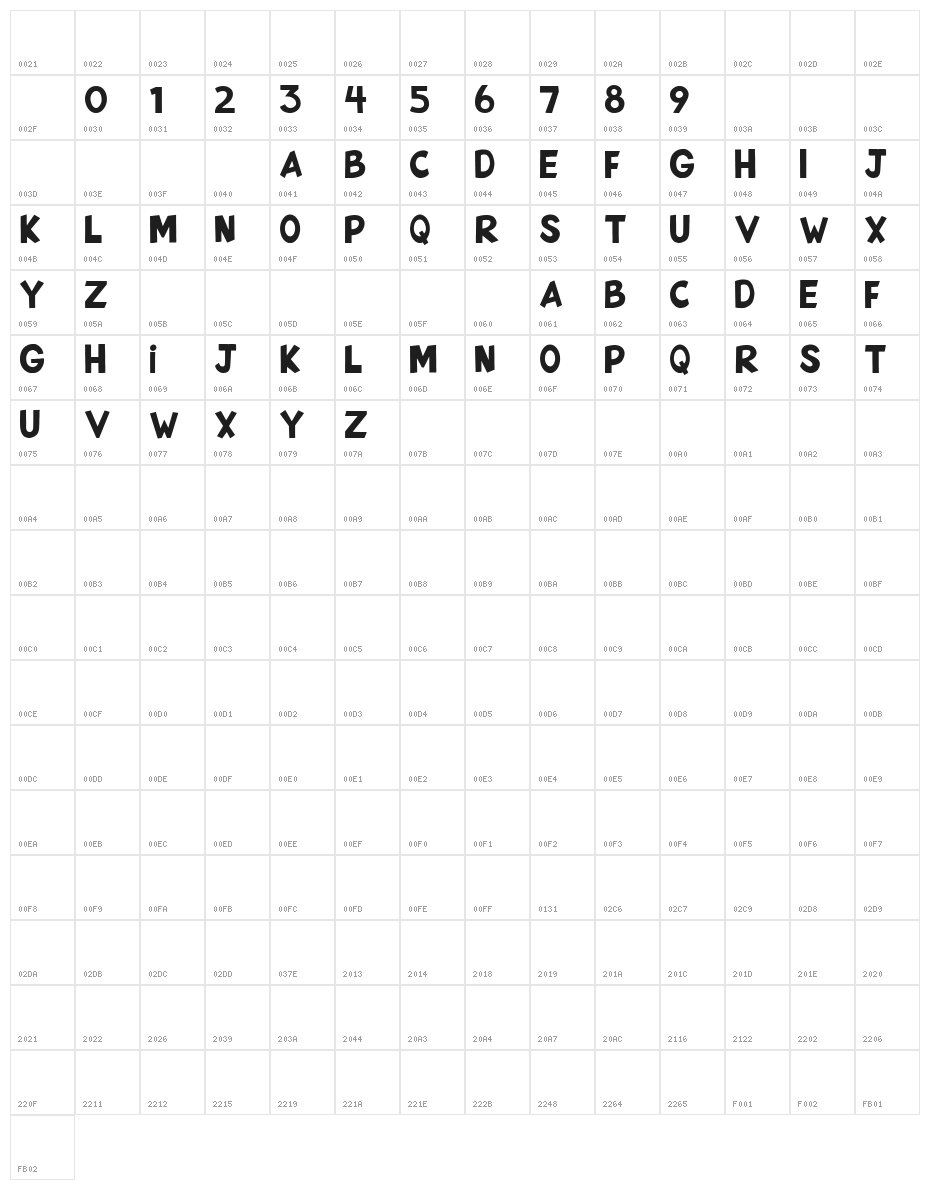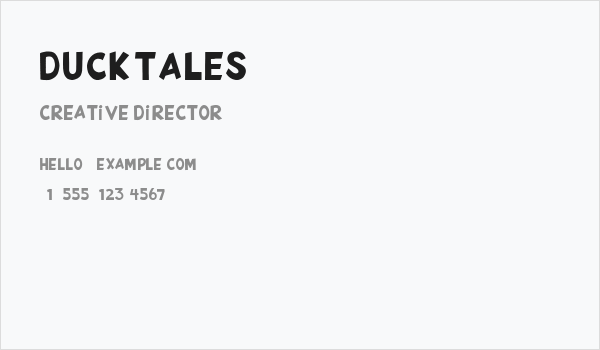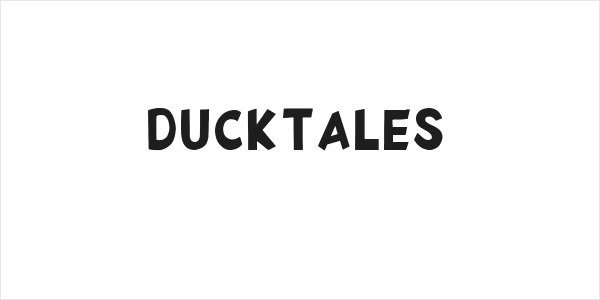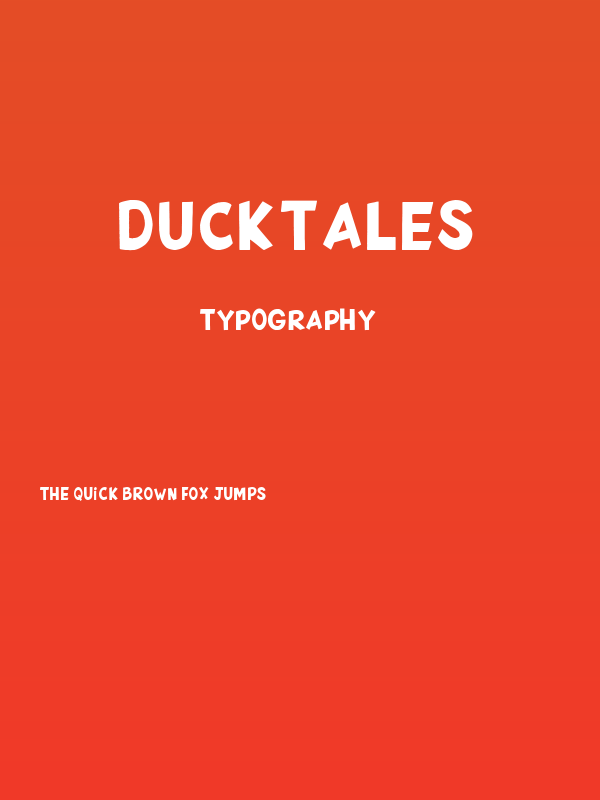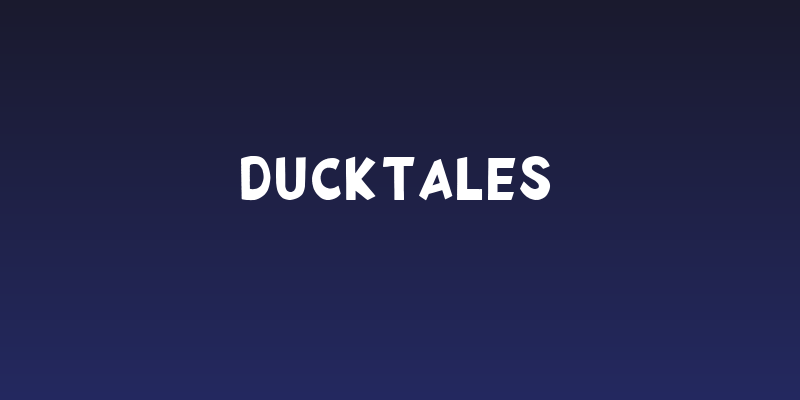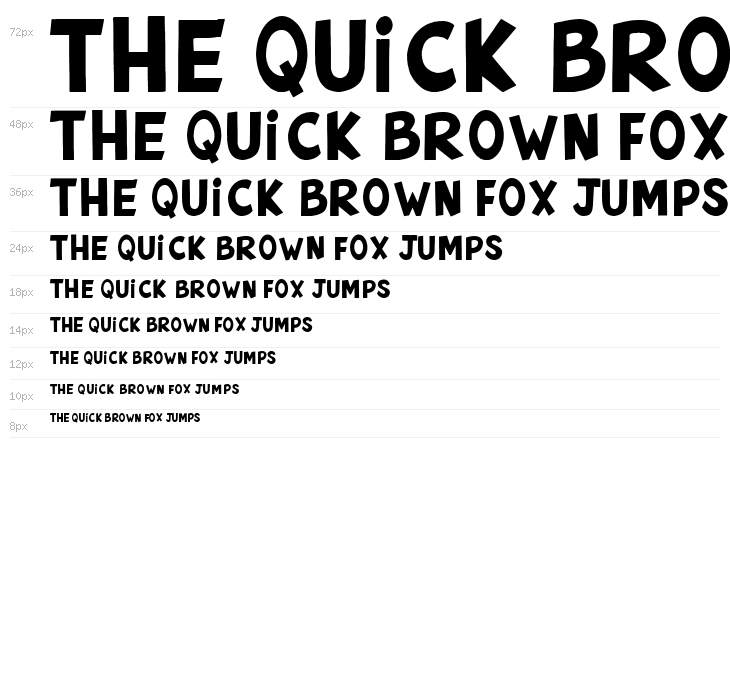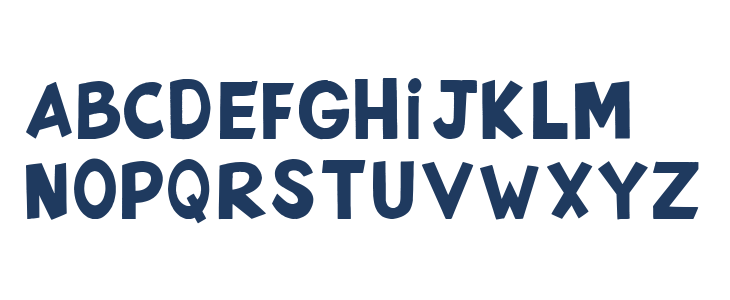
DuckTales Font
| 整体风格 | Playful, Whimsical, Energetic |
| 使用场景 | Headlines, Logos, Children's content |
| 推荐项目 | Ideal for children's books, cartoons, playful branding, and any project needing a fun, engaging aesthetic. |